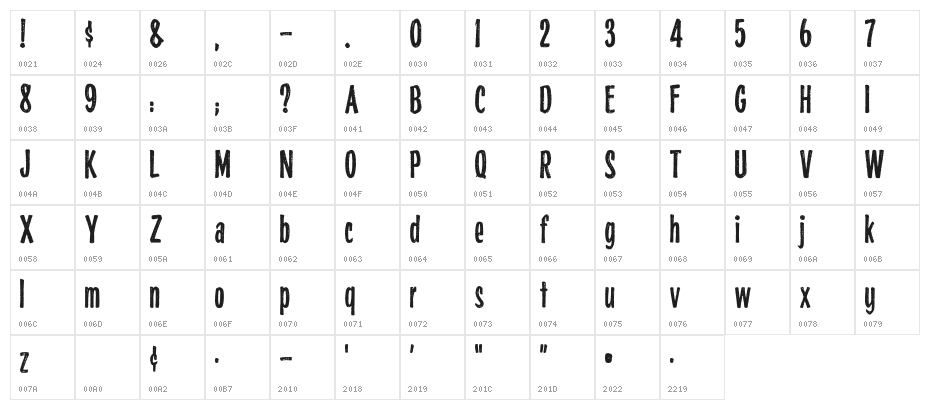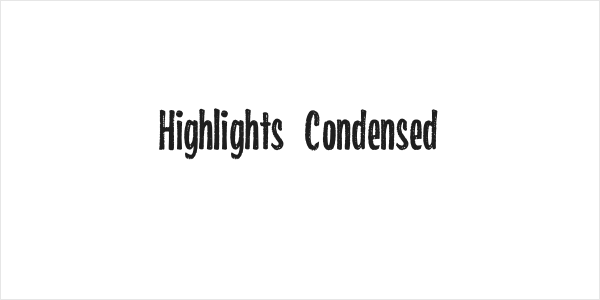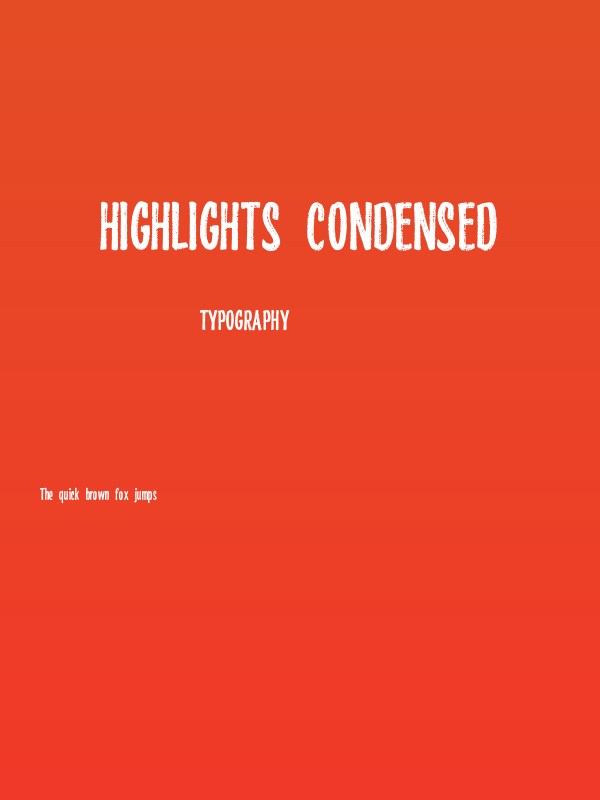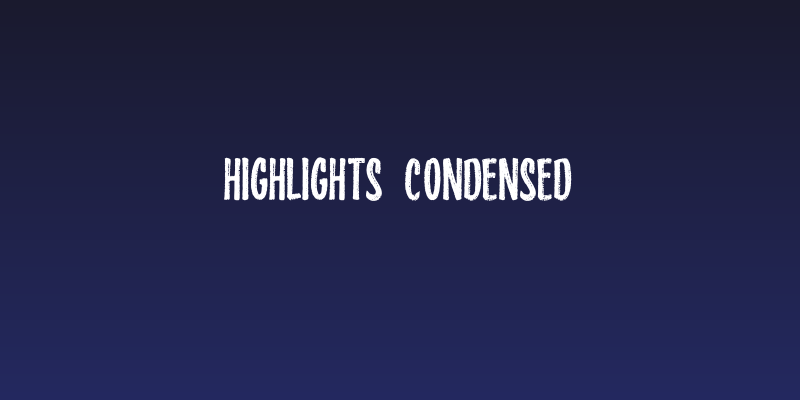
Highlights Condensed Font
✎ Messy
| Kategorien | Messy |
| Gesamtstil | Vintage |
| Vorgeschlagene Projekte | Ideal for vintage-themed posters, logos, and branding materials where a bold and rugged look is desired. |